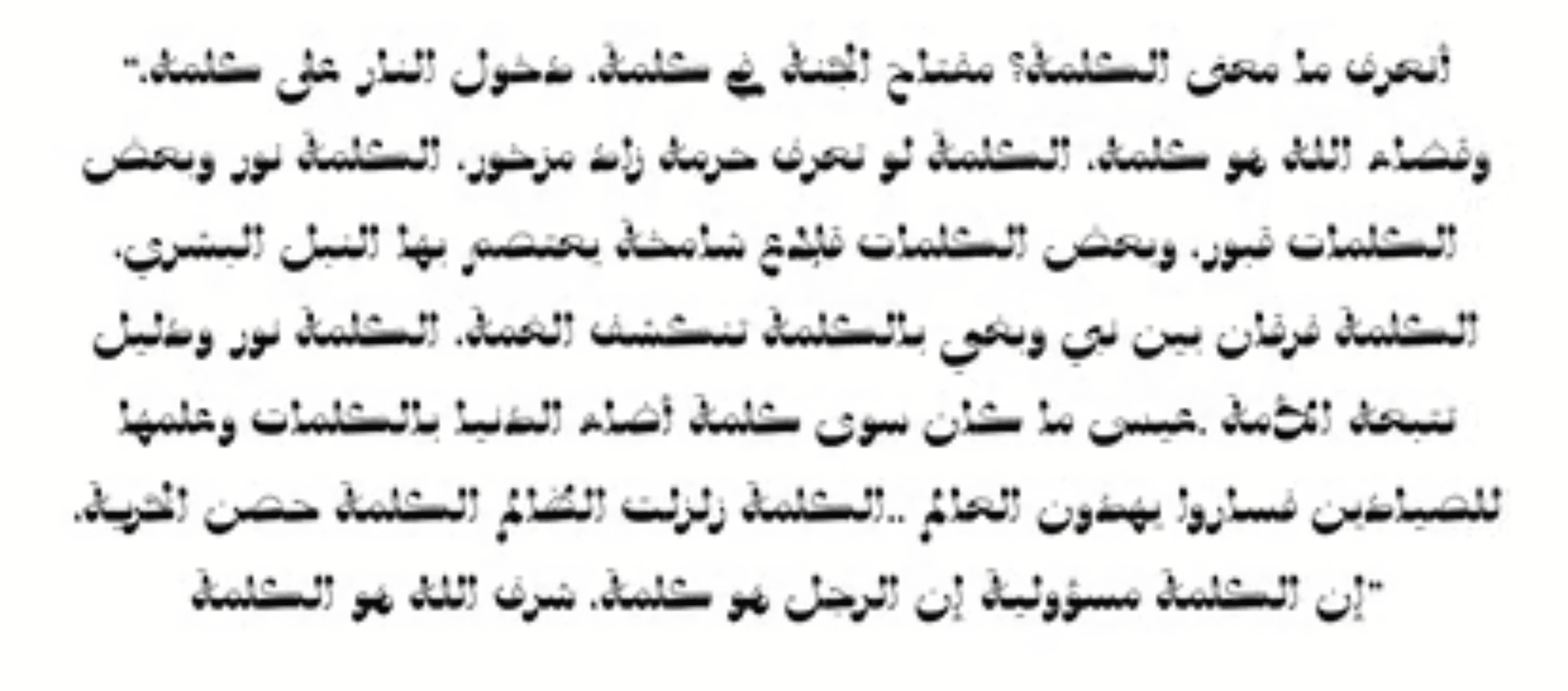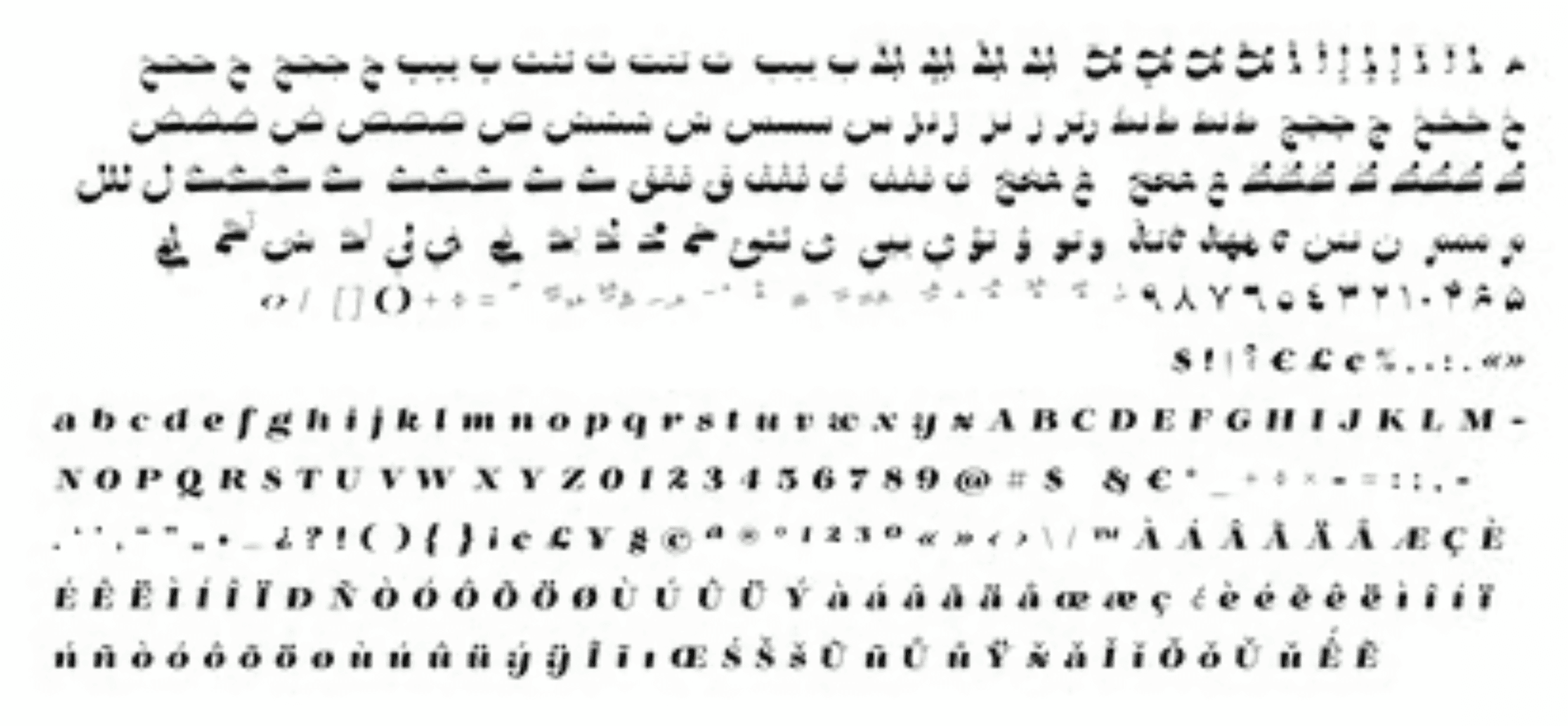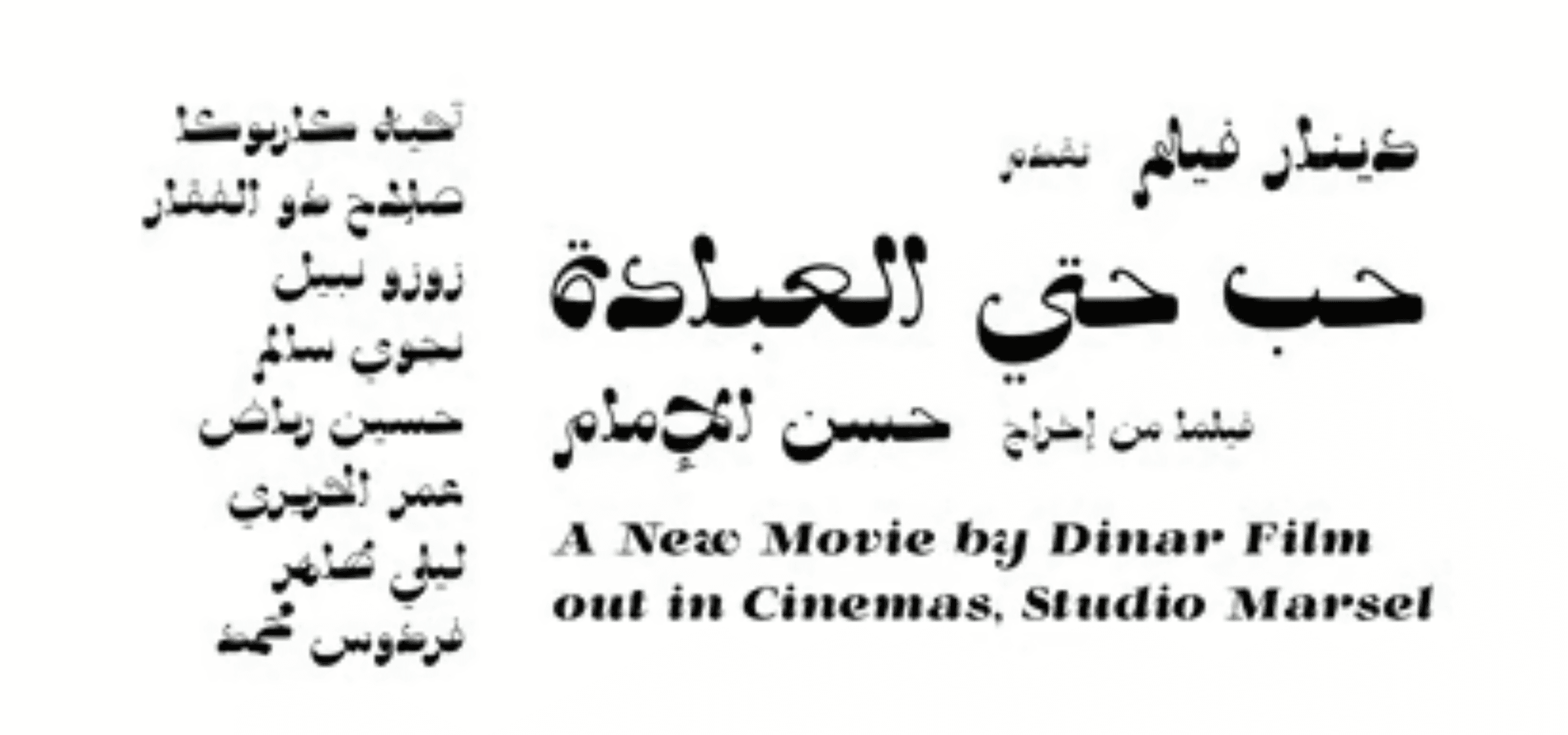
فوازير نيللي هو خط عرض ثنائي اللغة، يعتمد الخط العربي فيه على أسلوب الكوفي المغربي ويتميز بتباين كبير في سماكة الخطوط. أما الخط اللاتيني فهو مائل وعالي التباين، يتناغم مع الطابع العربي. يُستخدم بشكل مثالي في العناوين وتصميم الملصقات، ويجمع بين الأصالة والنكهة العصرية.